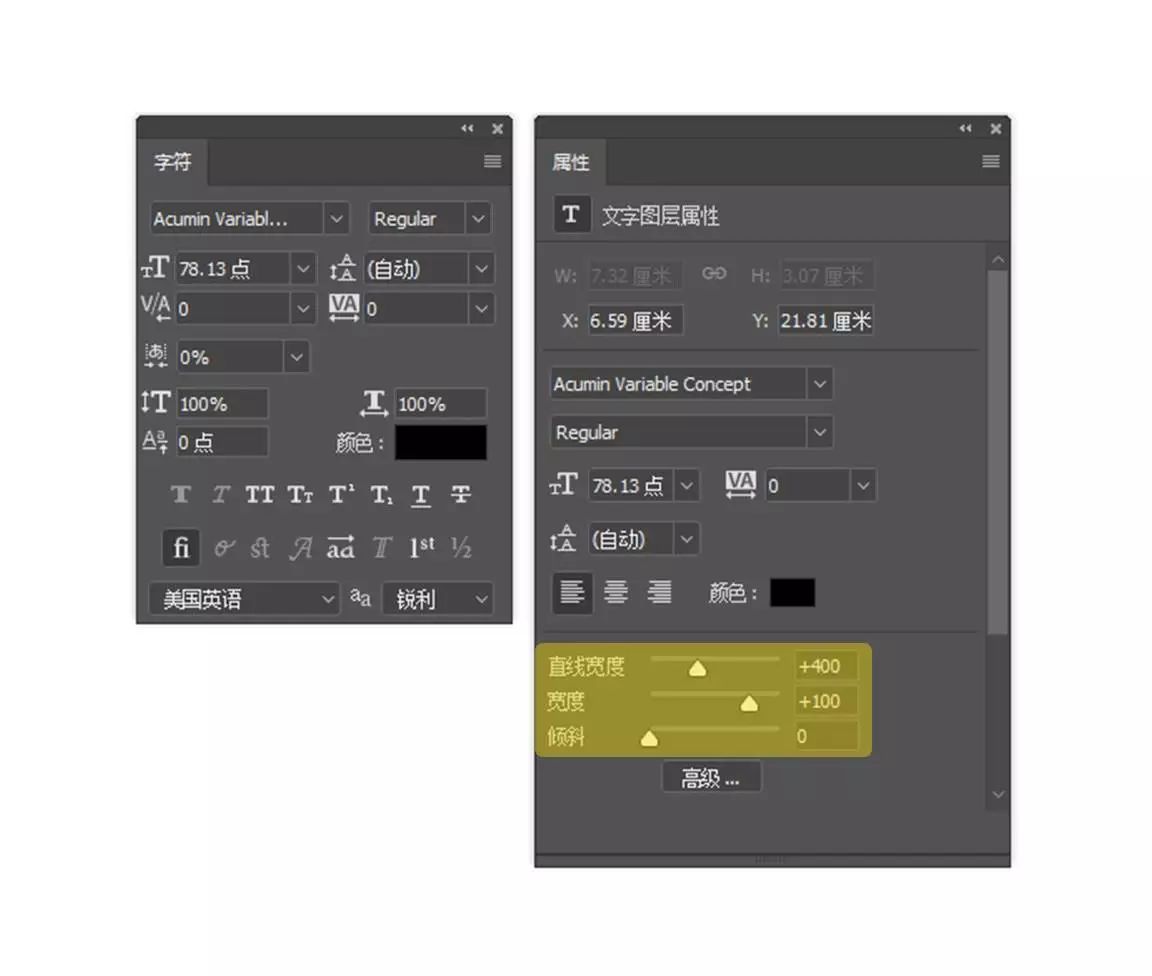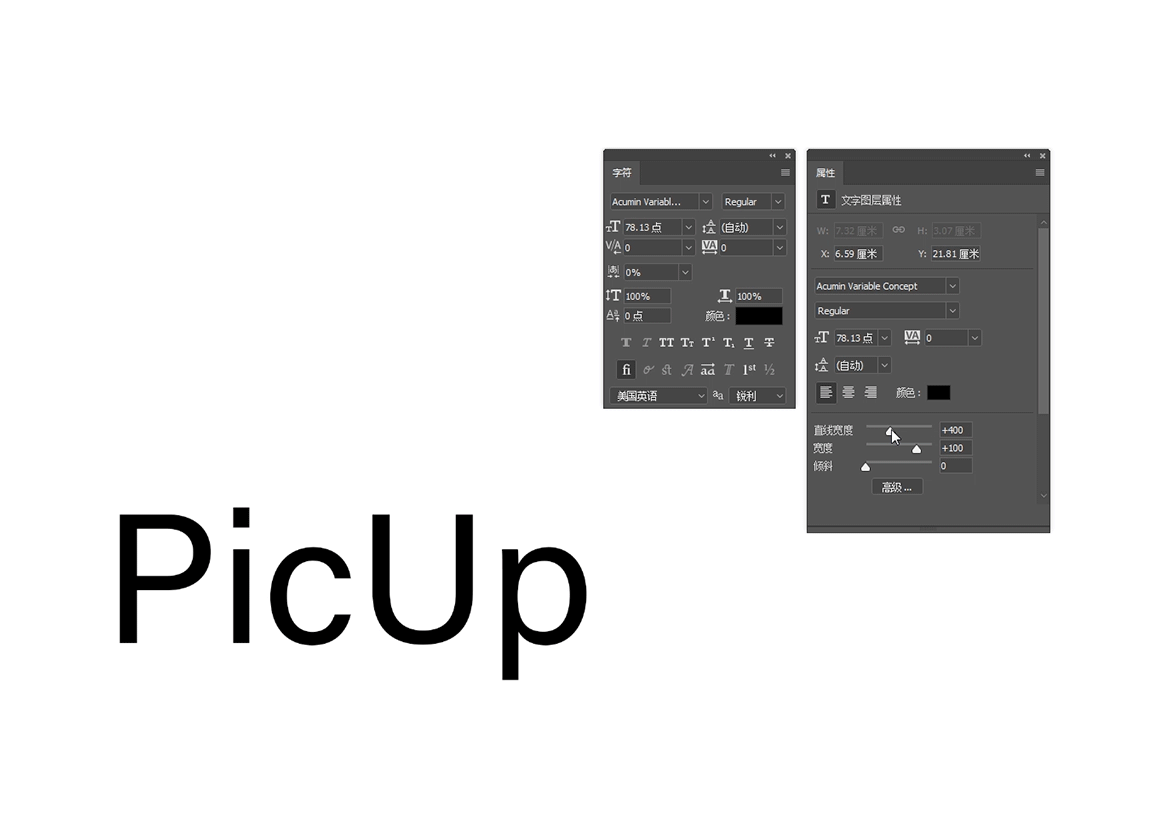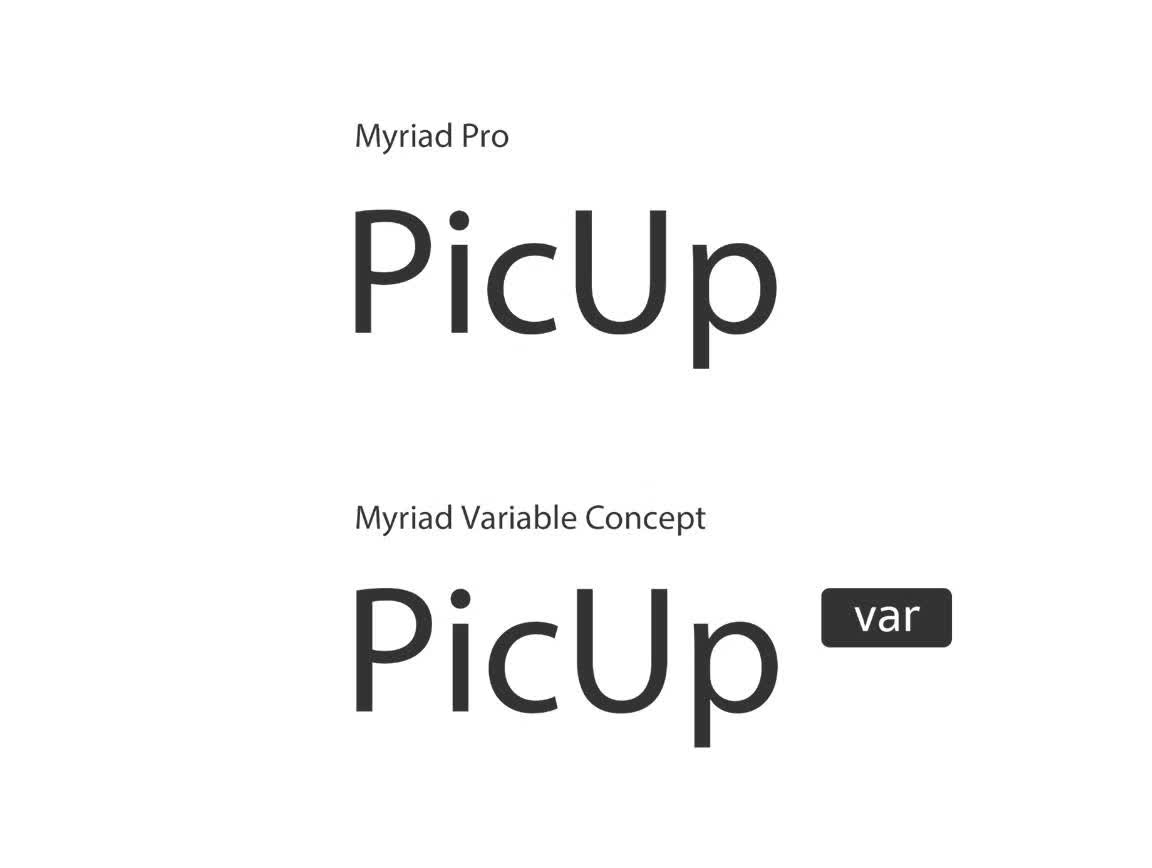
Ps CC 2018新特性系列教程Ⅰ--贴心的「可变字体」
Ps CC 2018相比2017多了不少全新的体验
有些功能简直
可以让你的工作效率提升数倍
从今天开始
我们就来逐一了解一下
这些新工具的全新特性和崭新的体验
Ps CC 2018中,新加入了一个对Variable font的支持特性,那么首先,我们来了解一下什么叫Variable font。
早在去年的9月(2016年9月),Adobe, Apple, Google, Microsoft 4大巨头企业联合宣布了全新的字体规范Variable Font,因此,从OpenType v1.8 之后,主流平台的操作系统,浏览器,制图软件以及多媒体应用和字体设计师都开始全方位的投入到了Variable Font的支持以及开发工作中。
符合Variable Font规范的字体开发过程也不算轻松,这些字体都需要字体设计师们精心的打磨细节,以及修正调整字体的变化参数,之后便是经过严苛的测试以及反复的修改,最终编辑出一套外框字型加外框控制点位移参数数据的特殊OpenType 字体文件。
Variable Font标准的成品字体制作完成后,就可以通过操作系统或浏览器的内嵌字型渲染引擎 (font engine)进行解析。这样,随着使用者应用的不同软件框架的调用自动执行,由Variable Font的这种特殊规范变化出各种不同的字重、字宽或笔画形状等来做应用。
了解了Variable Font之后,作为最广泛的制图大户,Ps也总算在CC 2018正式支持了Variable Font。接下来就带你了解一下Variable Font在Ps中的使用方式吧。
首先打开Ps,当然要是CC 2018了^_^,然后我们到Ps中的字体库列表里找找,你会发现有些字体的预览前面有上图的这种VAR标示,这种字体就是符合Variable Font标准的字体文件了。
然后我就挑选了一组最有代表性的Myraid字库作为对比字,这两套字都同属于一款字体,只不过后者采用了最新的Variable Font标准,分别用这两套字输入相同的文字后,字面上看是没什么区别的。
当我们打开属性面板的时候(窗口 > 属性),仔细观察一下上面两款字库的属性面板,你会发现Variable Font的字体在属性面板下多了几个调节滑块,这些就是Variable Font的特殊属性了,而普通标准的字库是不会出现这些控制滑块的。
通过拖动这些滑块,可以清晰的看到字体的变化。
Variable Font字体的属性不仅限于“直线宽度”与“宽度”,有些Variable Font的字体还会有“倾斜”属性,比如上图我们挑选的这个字体,它就附带了“倾斜”的属性调节。
不同的Variable Font内嵌的调节属性也不尽相同,相信今后还会有更多的属性增加到这个标准中来。
Ps CC 2018除了对Variable Font标准的字体支持外,还有一个针对字体操作的小功能,很可能你还没有注意到,这里也借此机会介绍给你们。
为了方便各位小伙伴看的很清楚,上图我们随意的挑选了四个不同字体组成文字。
接下来仔细看我们来做的一个操作,框选下行前面的文字信息,复制。
然后我们直接选上行的文字,进行粘贴替换,会发现文字信息是复制过去了,但是相应的,下行被复制信息所选用的字库也会被相应的复制过去,如果你还想用原来的字库文字,就需要在手动框选上这个字,然后切换字库……确实很不方便。
如果你粘贴的时候,不是用Ctrl+V来粘贴,而是右键,你可以看到弹出菜单中多了一个选项叫“粘贴且不使用任何格式”,点击这个来粘贴,就会只粘贴文字内容信息而不粘贴被复制信息所选用的字库。
这个新的小特性还是相当贴心的,确实弥补了之前Ps对于文字操作的一些不便之处。
Ps CC 2018的贴心小特性